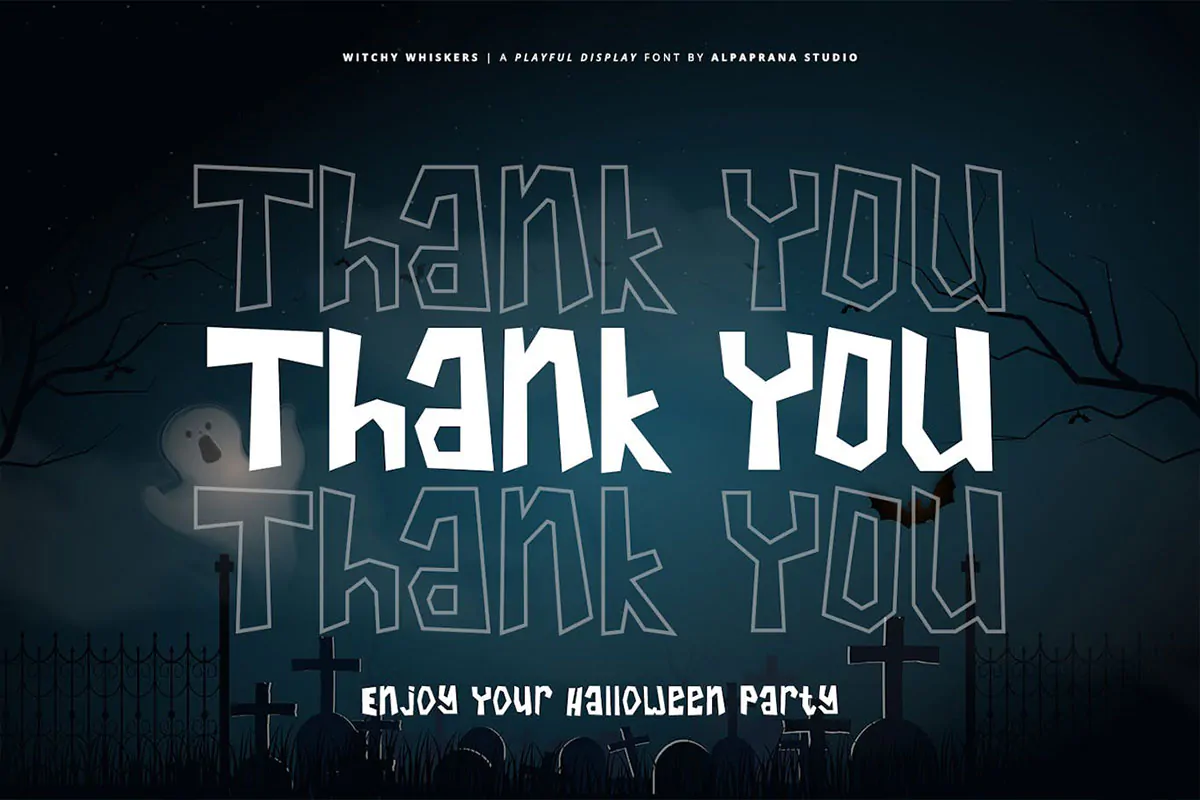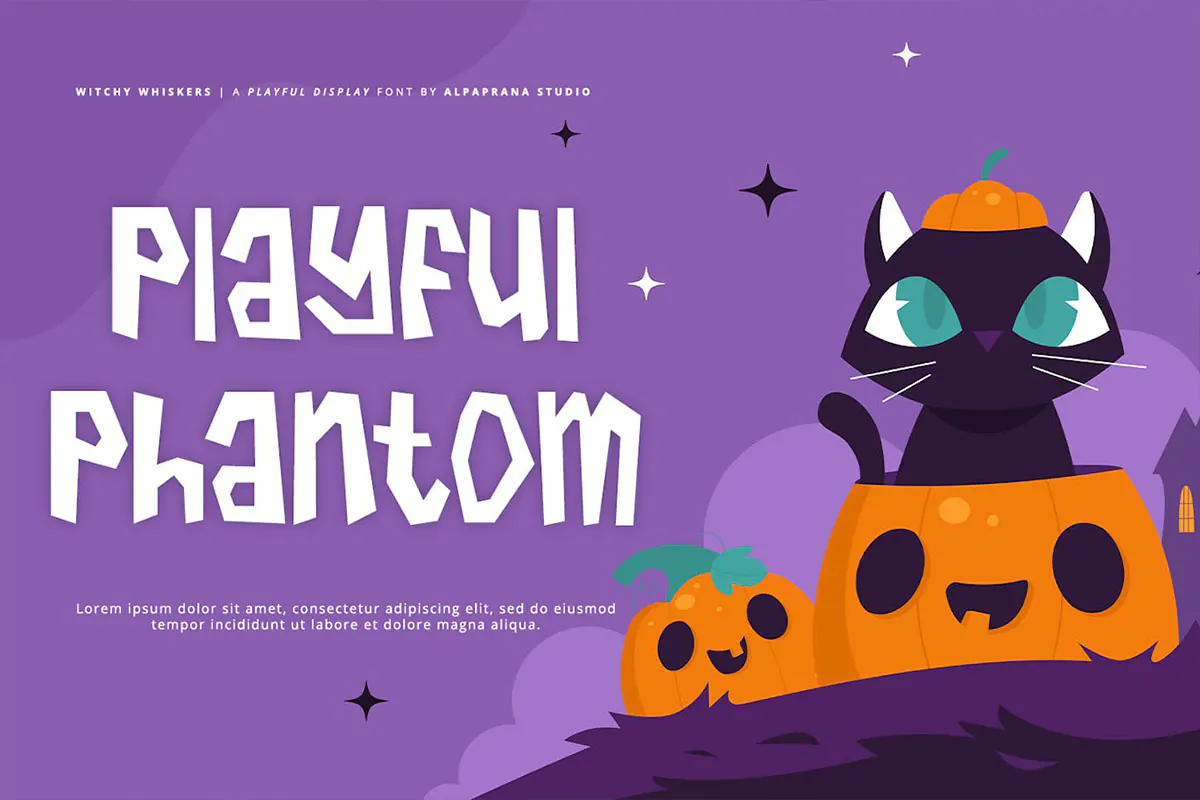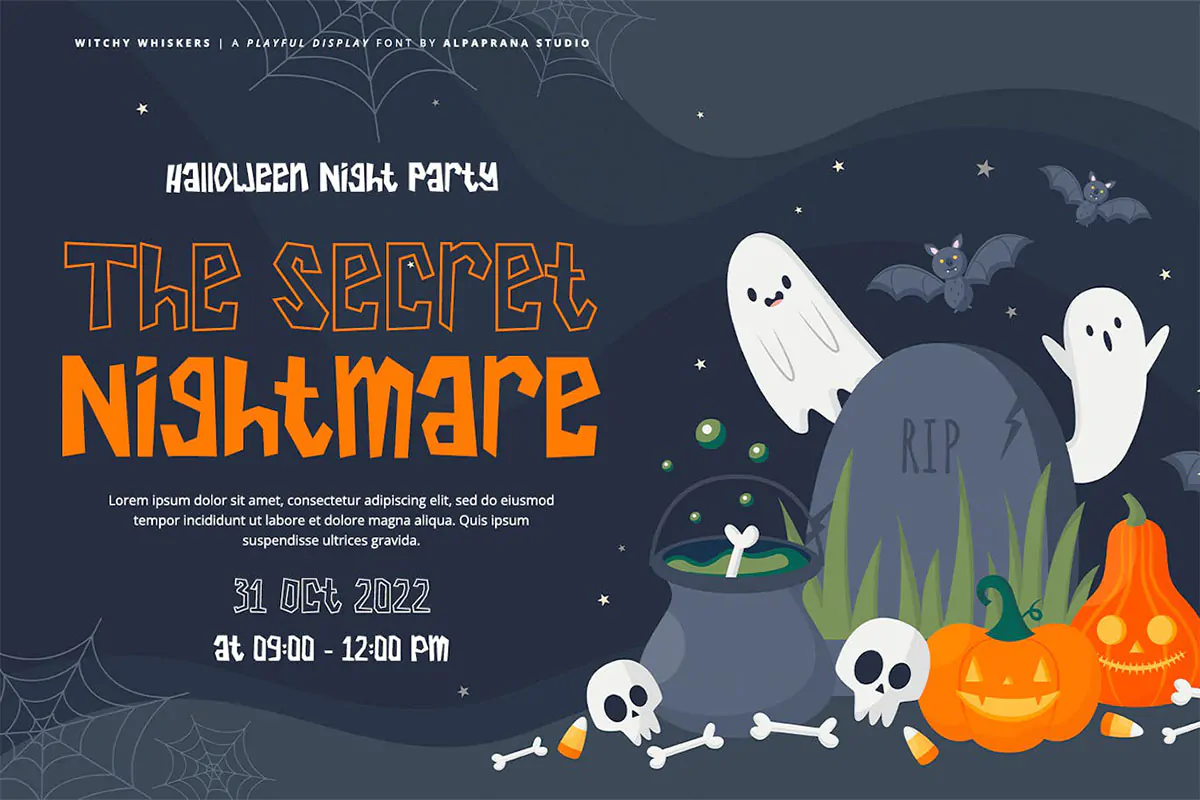
فونت ترسناک کودکانه Witchy Whiskers
فونت ترسناک کودکانه
فونت ترسناک کودکانه Witchy Whiskers یک قلم فوق العاده زیبای انگلیسی است که به صورت زاویه دار طراحی شده است و مناسب برای طراحی انواع پوستر، بسته بندی محصولات، بروشور، تراکت و … میباشد.